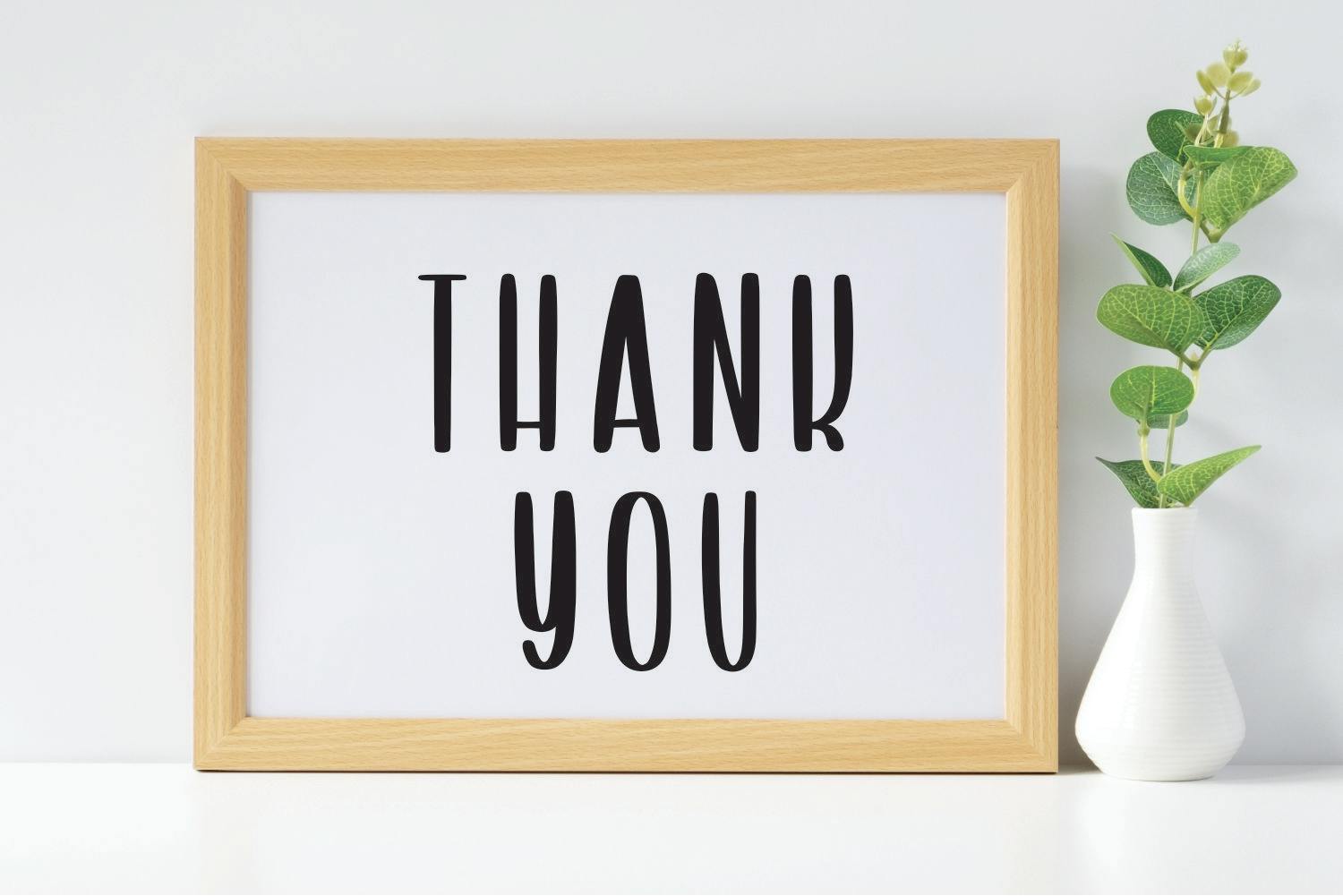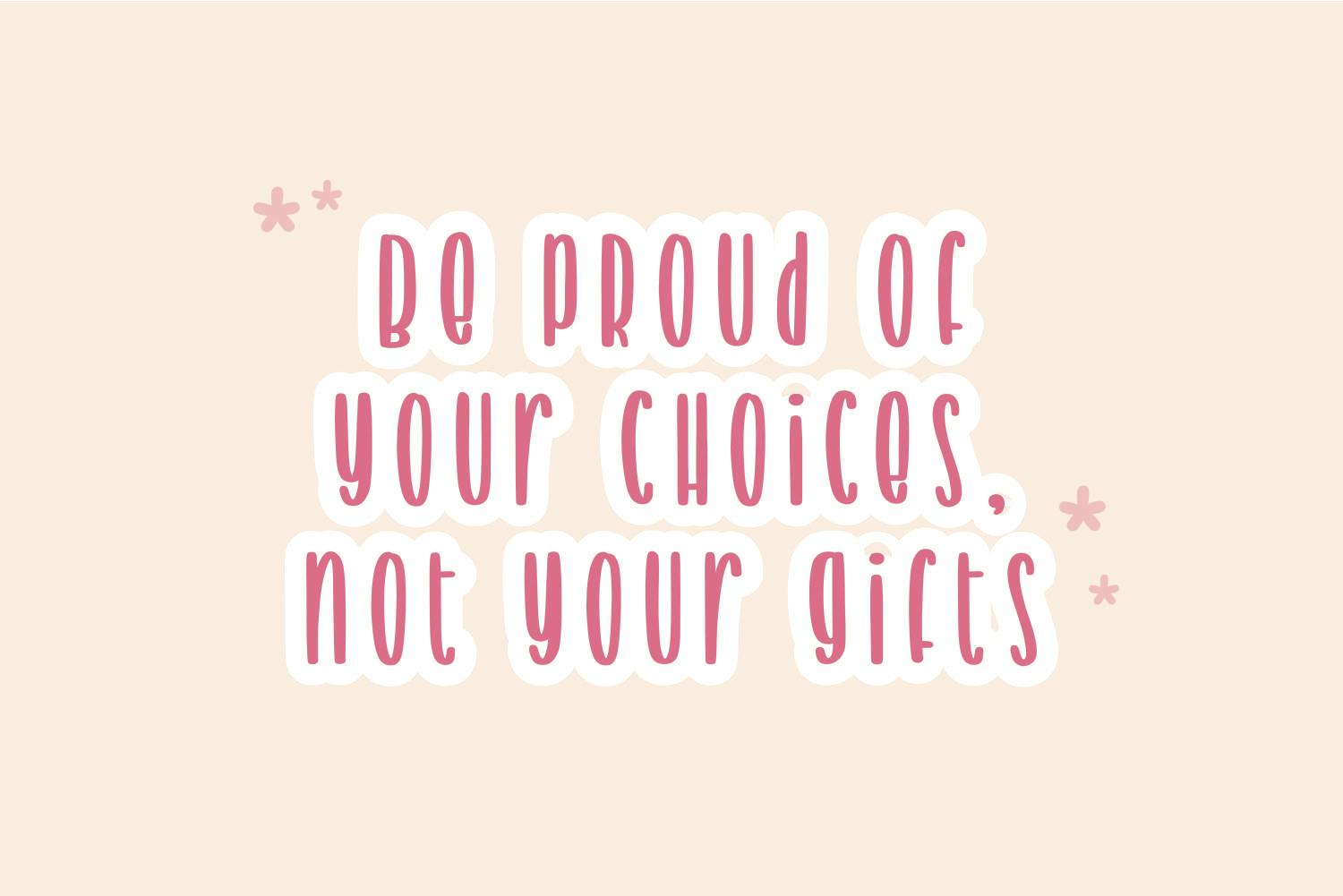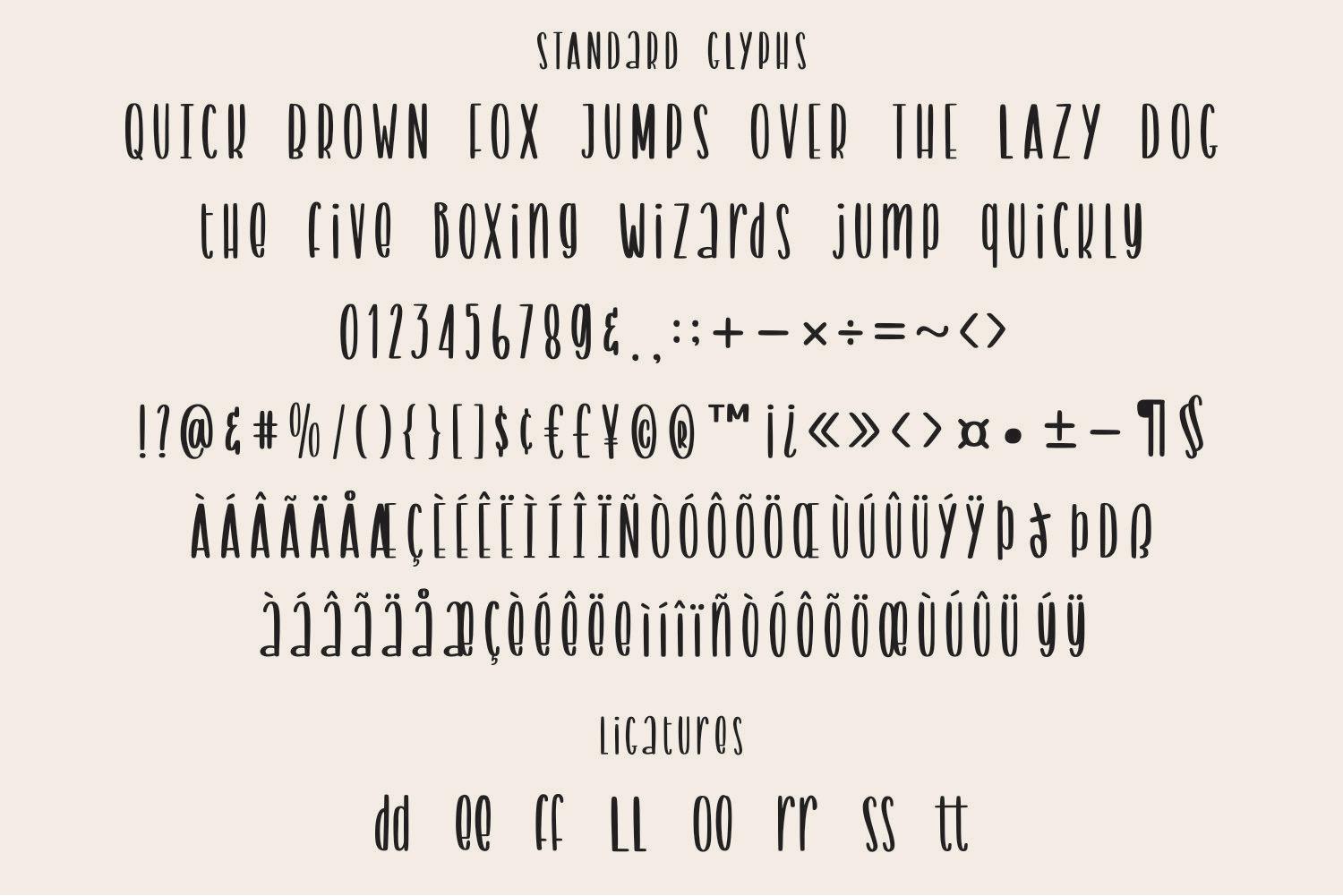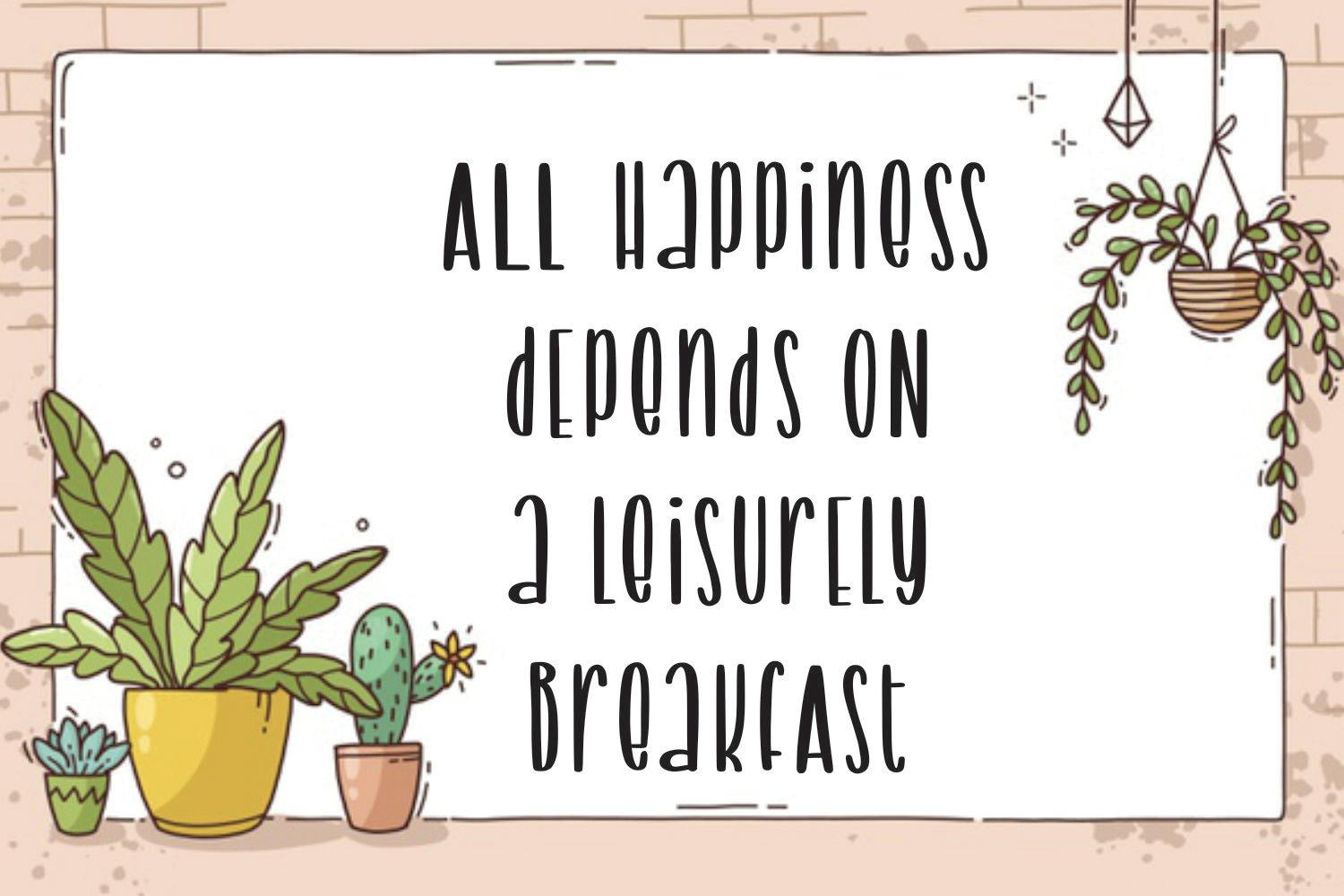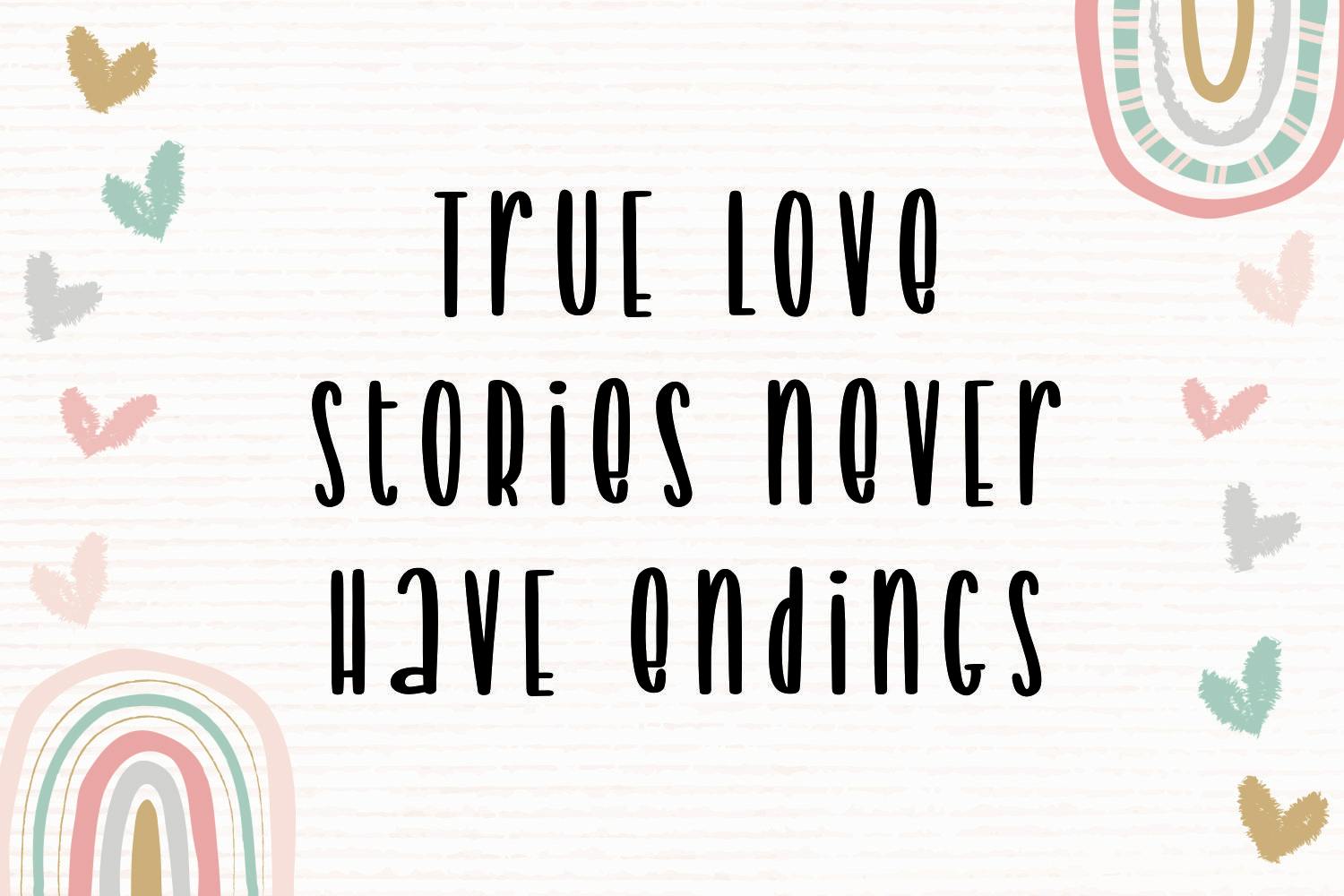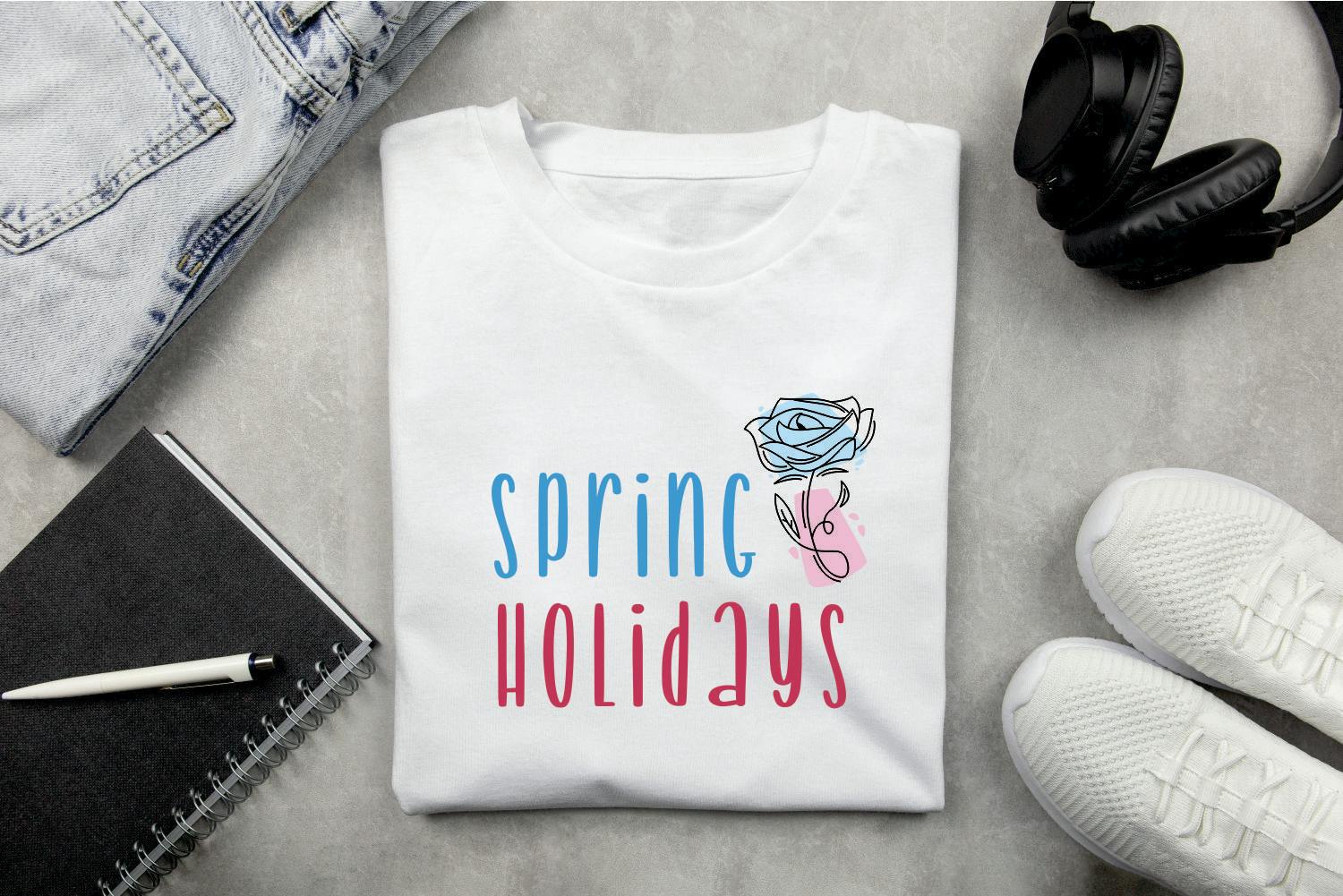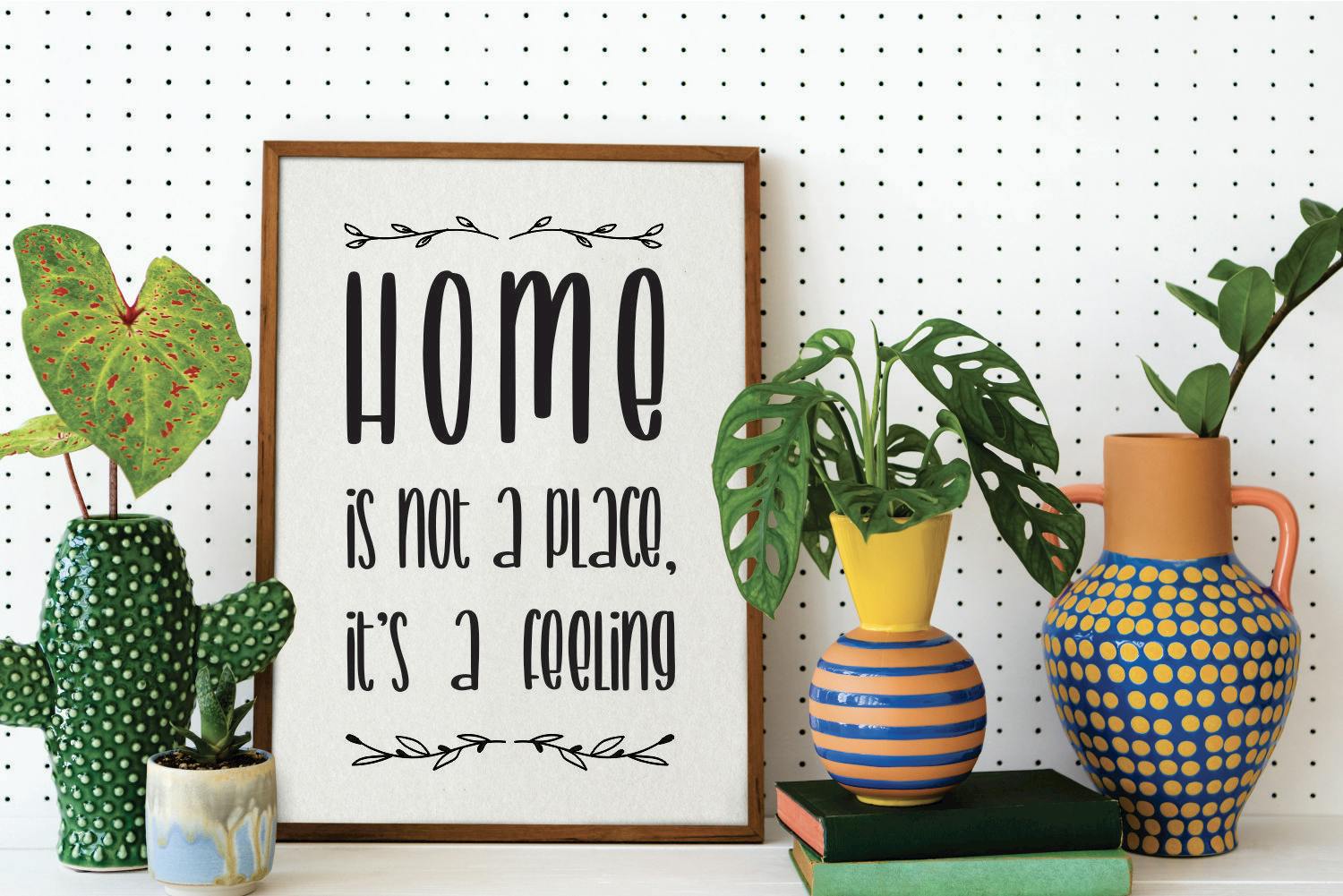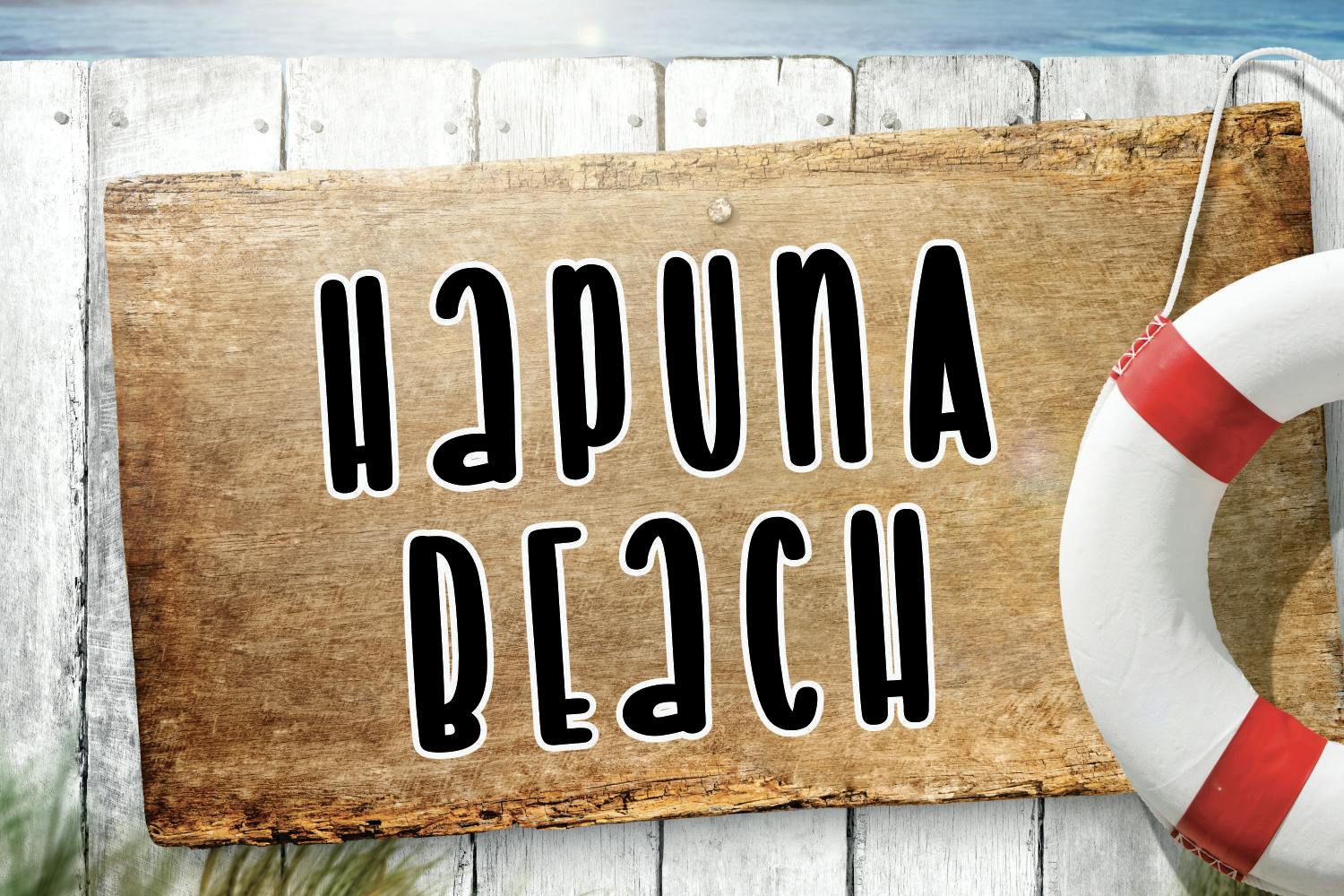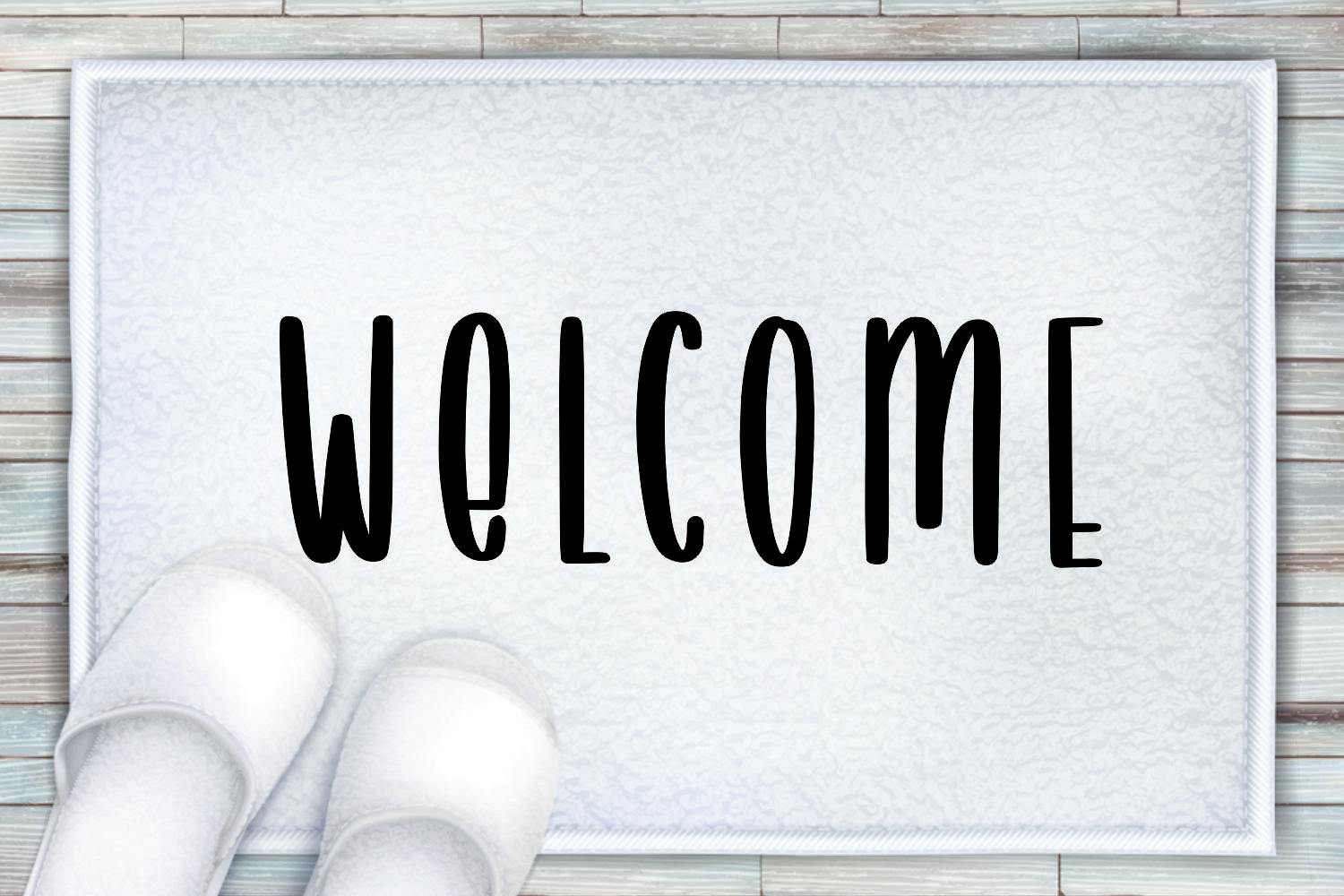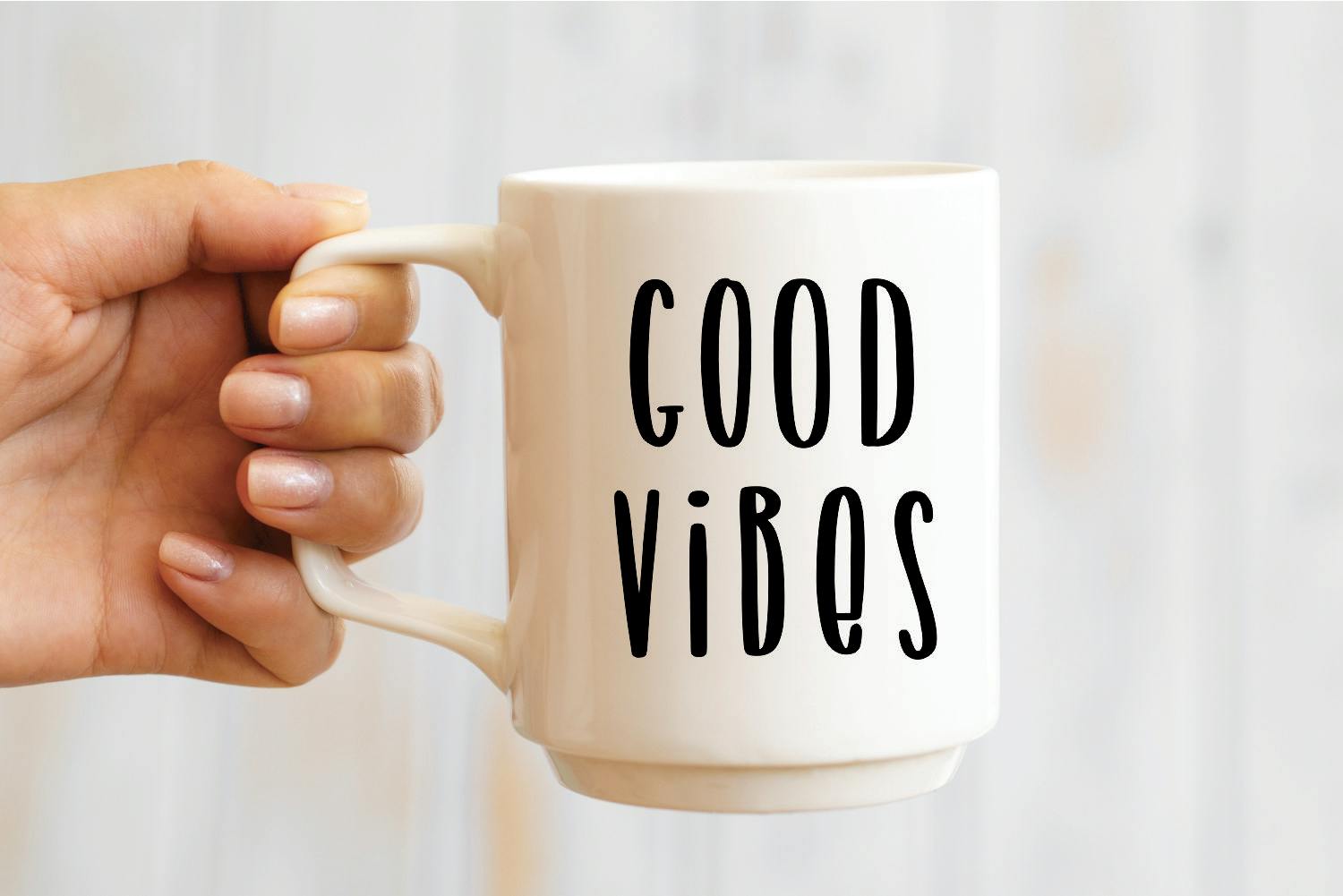
فونت ChickeN SandWich یک فونت دستنویس جذاب و سرگرمکننده است. این فونت به صورت PUA کدگذاری شده است که به شما این امکان را میدهد تا به راحتی به تمام گلیفها و تزئینات آن دسترسی داشته باشید!
این فونت برای کاردستی، برندینگ، دکوراسیون، طراحیهای مزرعهای، تیشرتها، طراحیهای SVG، وبلاگها، لوگوها، دعوتنامهها و موارد دیگر ایدهآل است! همچنین با کمک این فونت میتوانید یک لوگو یا قاب زیبا برای منزل خود طراحی کنید. یا فقط از آن برای کسبوکار، جلد کتابها، لوازمالتحریر، بازاریابی، مجلات و غیره استفاده کنید.
از سبک فوقالعاده چندمنظوره این فونت عاشق خواهید شد و میتوانید از آن برای ایجاد طراحیهای شگفتانگیز استفاده کنید! از این فونت برای هر پروژه کاردستی که نیاز به ظاهری شخصیسازی شده دارد، بهره ببرید!